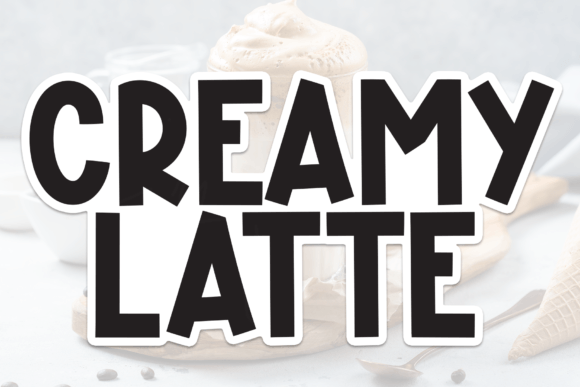
Creamy Latte Font
Creamy Latte Font – أناقة ودفء في كل حرف
أضف لمسة من الرقي والدفء إلى تصميماتك مع Creamy Latte Font، الخط المثالي الذي يجمع بين الأناقة العصرية واللمسات الكلاسيكية الناعمة. يتميز بتصميمه الانسيابي وحروفه المتناغمة، مما يجعله مثاليًا لمجموعة متنوعة من الاستخدامات، مثل:
☕ تصميم الشعارات والهويات البصرية
✍️ دعوات الزفاف والمناسبات الخاصة
????️ تغليف المنتجات والعلامات التجارية
???? منشورات السوشيال ميديا والتصميمات الرقمية
يمنحك Creamy Latte Font القدرة على التعبير عن أسلوبك الخاص بلمسة من الفخامة والدفء، تمامًا مثل فنجان اللاتيه الكريمي في صباح هادئ. احصل عليه الآن وأضف لمسة من الإبداع إلى أعمالك!